AA아키그룹은 1965년 현대건설 건축부에서 출발해, ‘신뢰’와 ‘혁신’을 바탕으로 건축 시장을 선도해온 글로벌 건축 그룹입니다. 뉴타입은 CI, 기업 브로슈어, 웹사이트 전 영역을 아우르는 리브랜딩 프로젝트를 통해 AA아키그룹의 브랜드 아이덴티티를 새롭게 정립하였습니다. 이번 리브랜딩은 단순한 시각 체계를 넘어, AA아키그룹이 지향하는 철학과 미래적 방향성을 담아낸 전략적 커뮤니케이션 수단으로 자리매김하였습니다.
AA archigroup - Rebranding
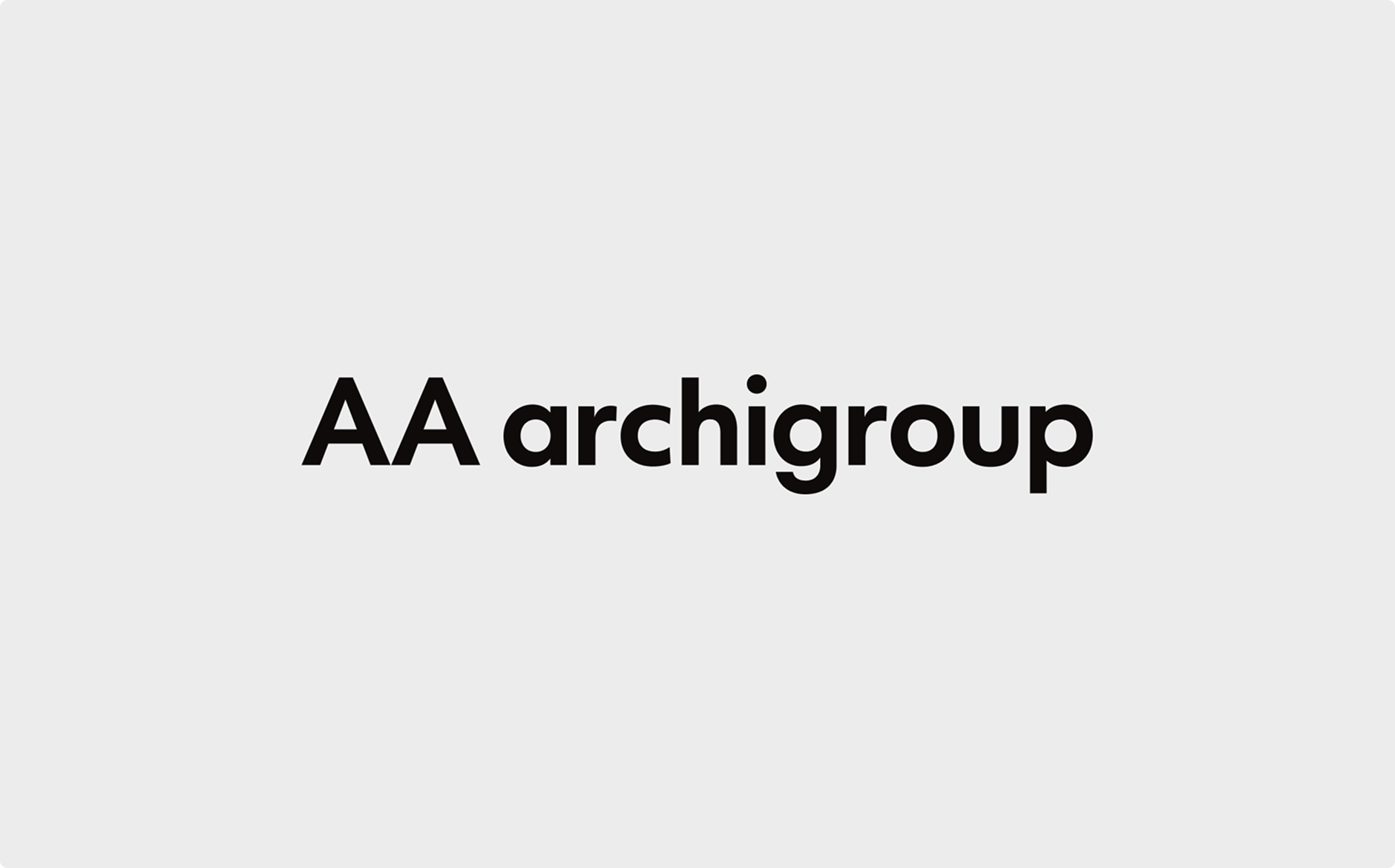
Trust & Innovation,
글로벌 건축 그룹의 미래를 담은 리브랜딩
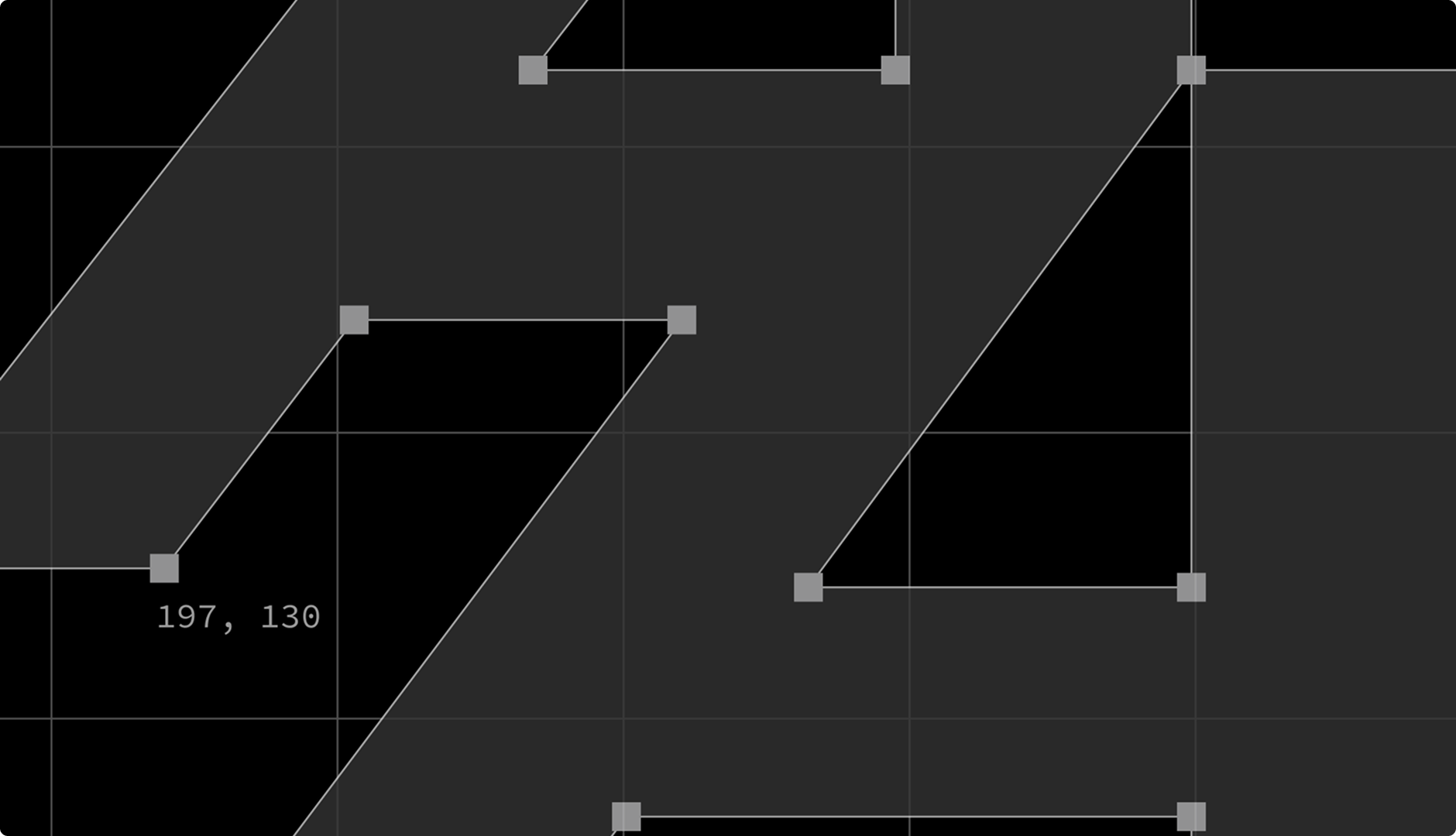
Advanced & Artistic
지난 60년간 축적된 하이테크 기술력과 통합 건축 솔루션은 AA아키그룹만의 핵심 경쟁력입니다. 뉴타입이 새롭게 정립한 브랜드 메세지, 'Advanced & Artistic'은 고객 신뢰 바탕의 기업 비전을 이러한 핵심 경쟁력과 함께 담아냅니다. 이를 바탕으로 기존 브랜드 컬러와 CI를 글로벌 건축 그룹으로서의 현대적인 이미지로 재해석하고, 볼드한 모노톤의 정제된 타이포그래피를 활용하여 일관된 브랜드 커뮤니케이션과 매체 간 활용도를 높이는 데 집중했습니다.
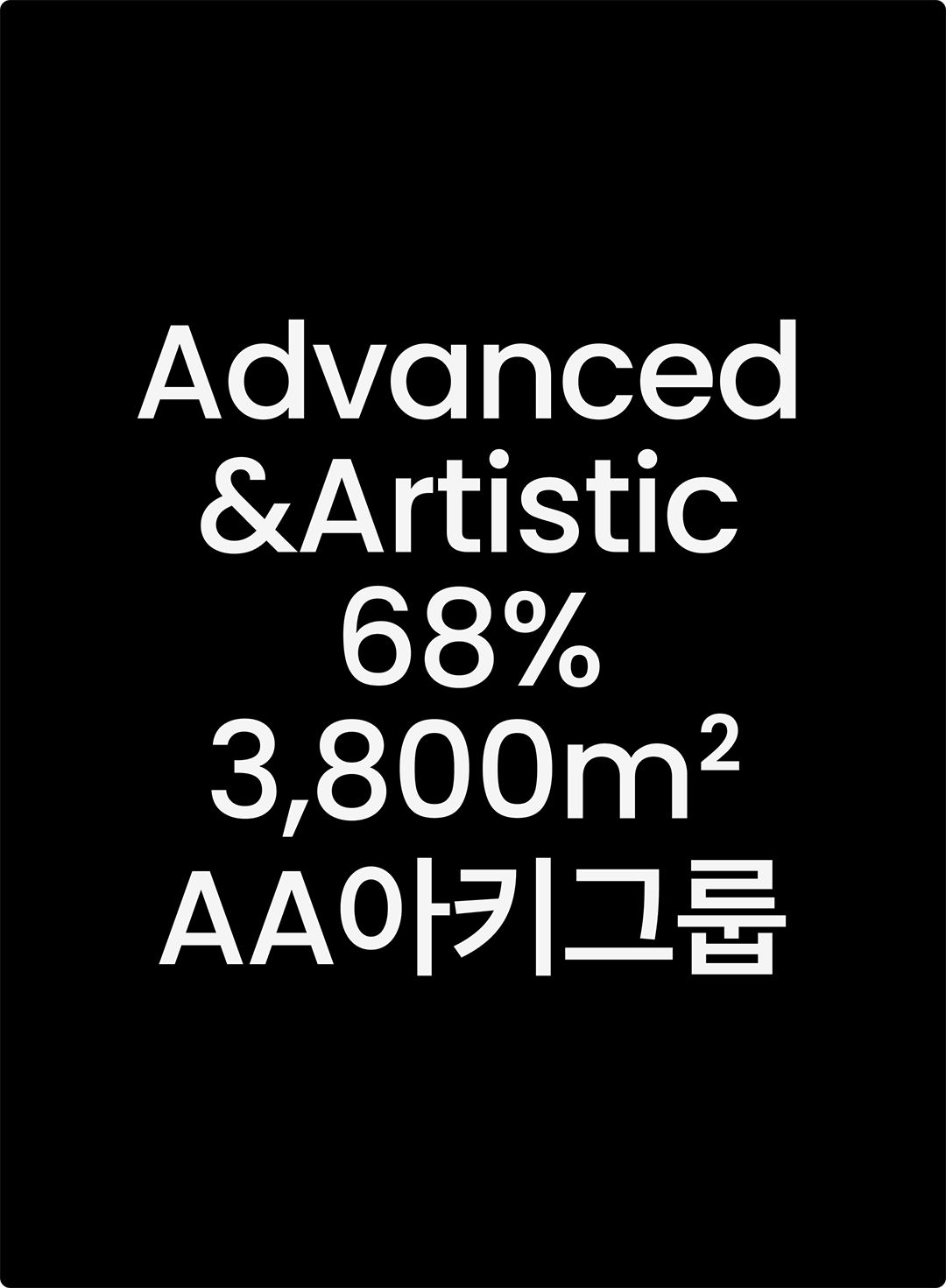
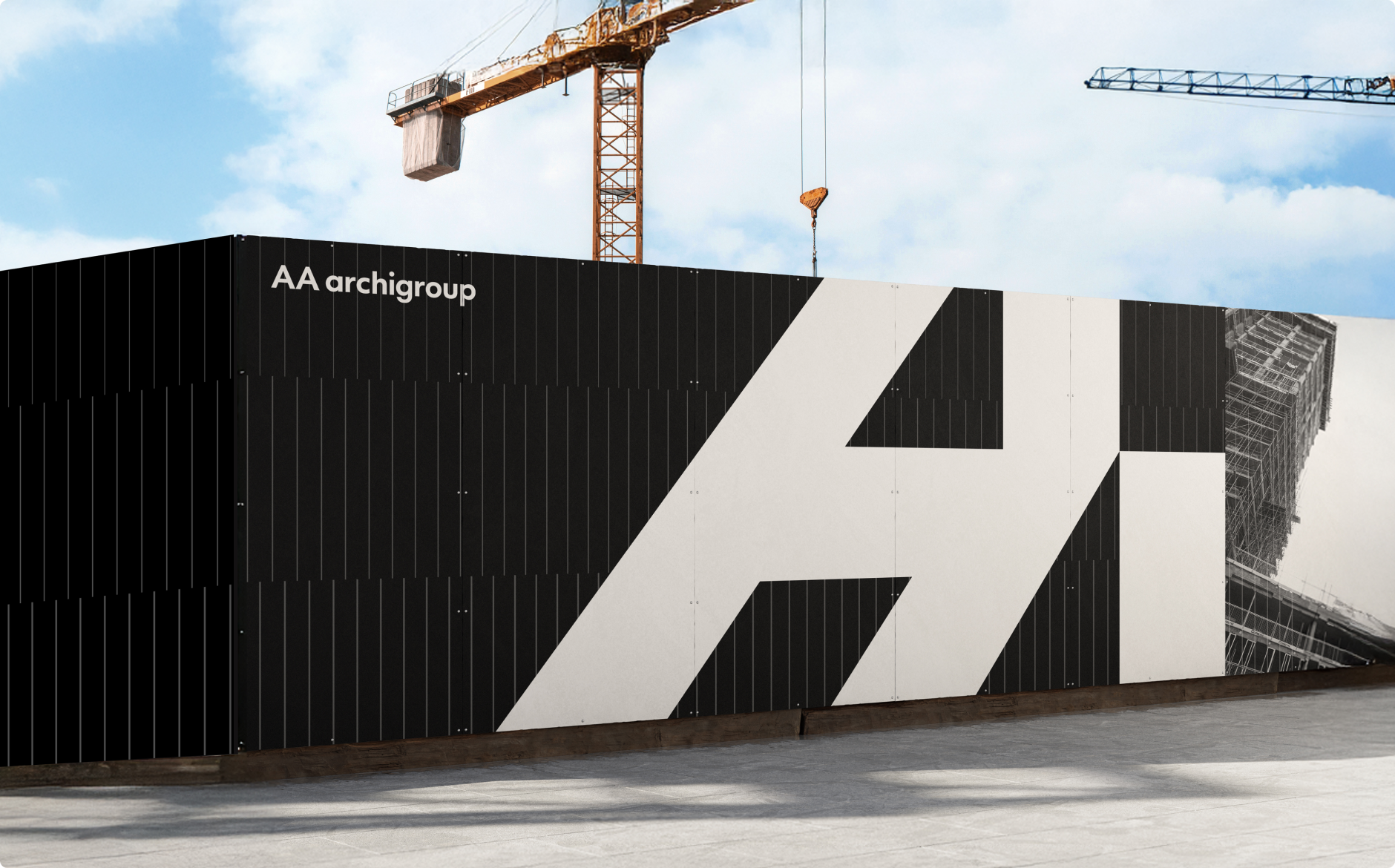
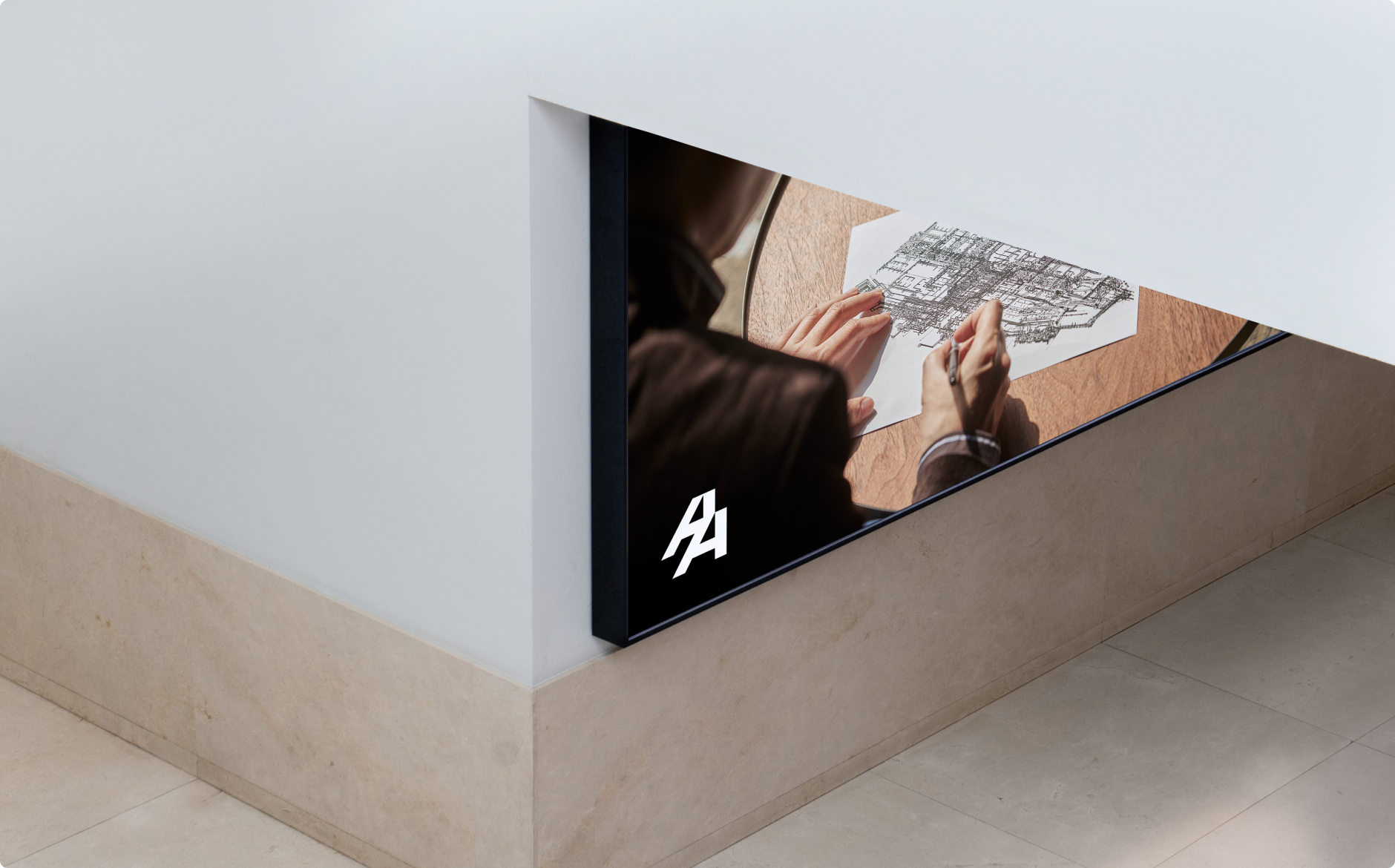
건축의 전문성을
시각화한 기업 브로슈어
AA아키그룹의 핵심 사업 분야와 주요 준공·설계 프로젝트는 브로슈어의 정제된 레이아웃과 텍스트 중심의 구조를 통해 명료하게 표현됩니다. 미니멀한 톤의 균형잡힌 그리드 디자인은 AA아키그룹만의 하이테크 기술력과 구성원들의 뛰어난 전문성에서 모티브를 얻어 정립되었습니다. 또한, 챕터별 레이아웃을 다르게 적용하며 사업 분야를 시각적으로 구분하면서도 모든 프로젝트가 균형 있게 드러날 수 있도록 구성했습니다.
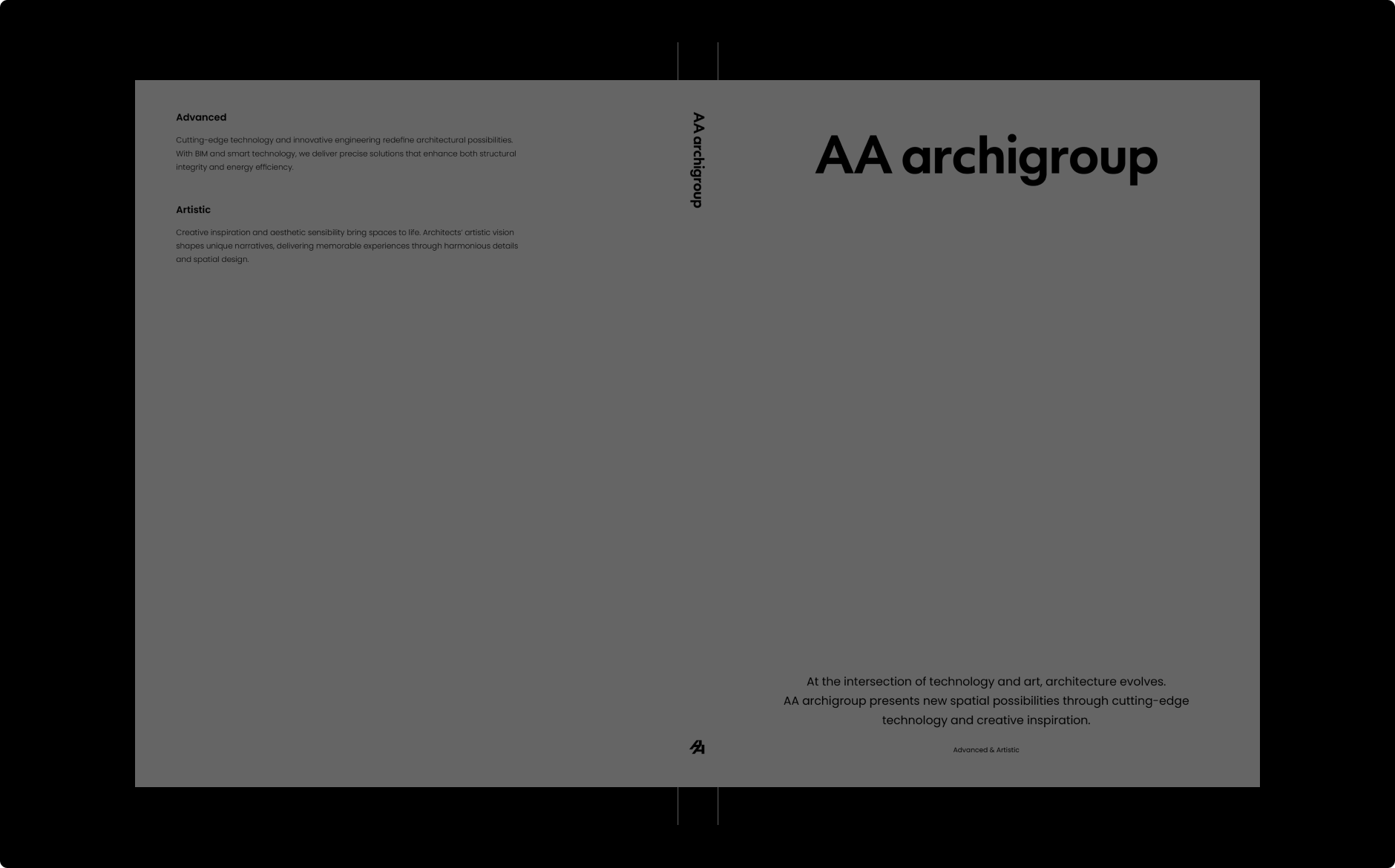
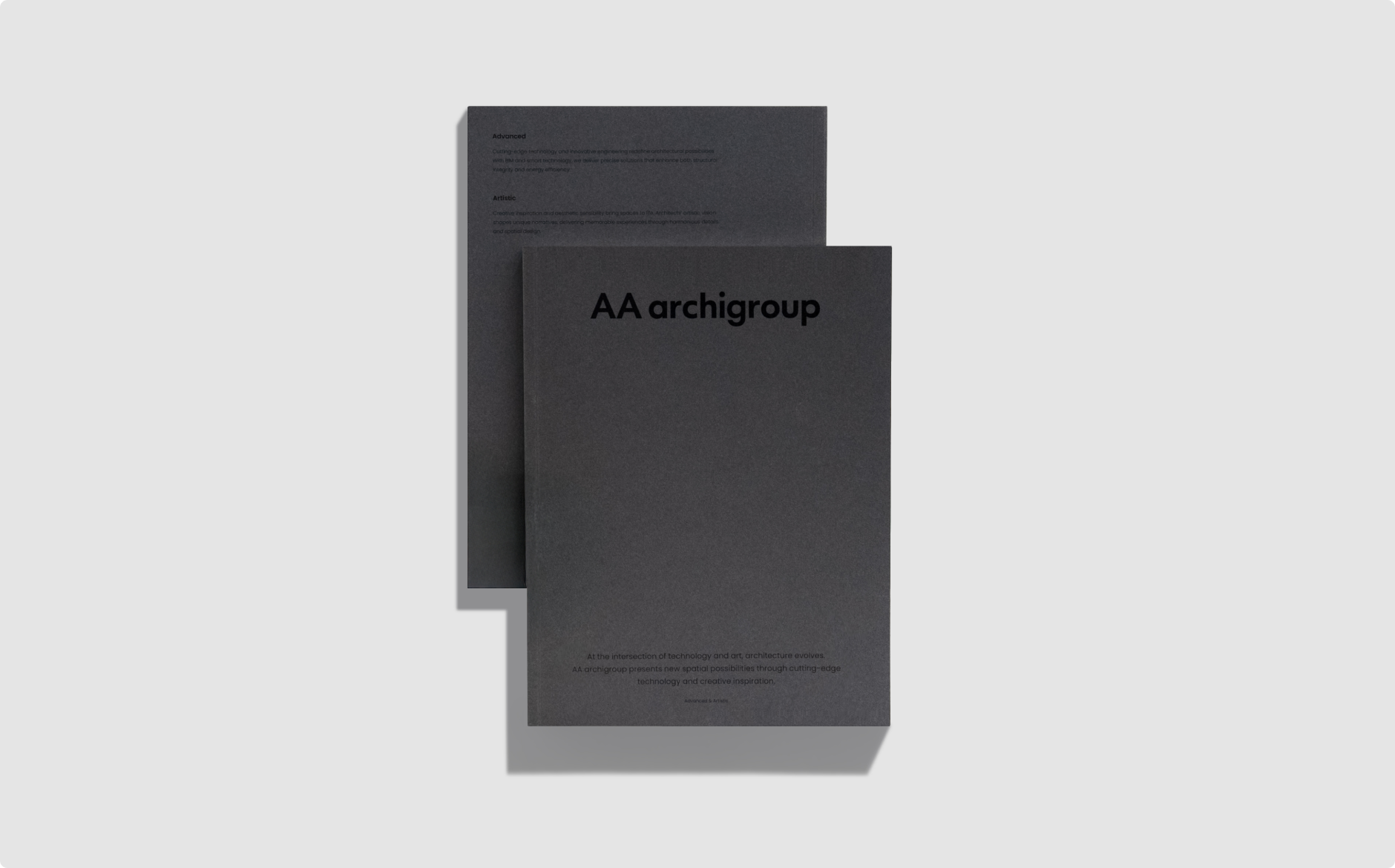
브랜드 철학을 반영한
웹사이트 개편
AA아키그룹의 기업 웹사이트는 다양한 사업 영역 간의 유기적 연결성과 혁신적인 하이테크 기술력을 시각적으로 반영합니다. 직관적인 정보 구조와 각 섹션의 특성을 반영한 자연스러운 인터랙션 요소는 브랜드 메세지를 명확히 드러냅니다. 이를 통해, 60년간 끊임없이 진화해 온 AA아키그룹의 건축 철학을 사용자에게 전달하고자 하였습니다. 섹션별 대표 이미지와 간결한 그래픽은 구성원의 리더십과 전문성을 신뢰감 있게 전달하며, 웹사이트 전반에 걸쳐 적용된 인터랙션 요소는 자연스러운 추가 탐색 경험을 지원합니다. 이에 Project, News 섹션은 사용자 편의성과 서비스 확장성을 고려한 '콘텐츠 카테고리 중심'의 디테일한 검색 필터 기능을 강화하며, 프로젝트 관련 이미지와 핵심 정보를 한 눈에 확인할 수 있는 직관적인 UX를 구현했습니다.